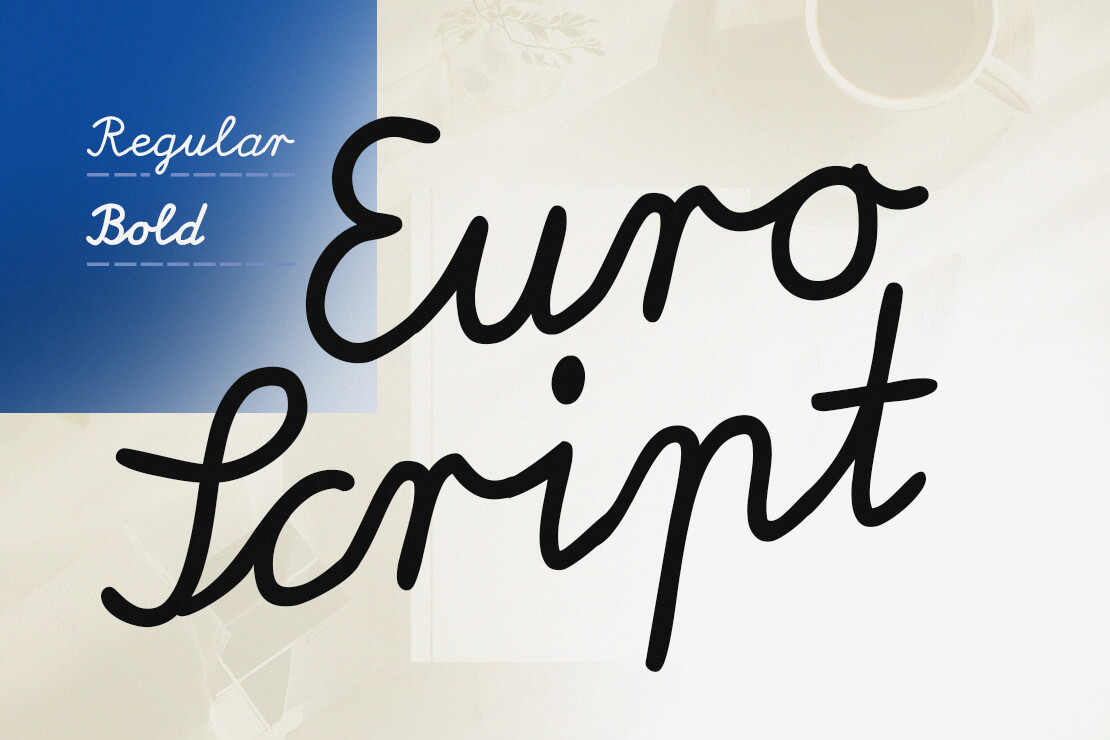
EuroScript
Mit der »EuroScript« stellt Peter Wiegel eine Schreibschrift zur Verfügung, die stilistisch auf der in Schulen gelehrten vereinfachten Ausgangsschrift basiert.
Anders als starre Lernschriften zeigt dieser Font jedoch den Charakter einer weiterentwickelten und deutlich erwachseneren Handschrift. Das Schriftbild bewahrt sich durch die verbundenen Buchstaben und leichten Unregelmäßigkeiten eine natürliche Anmutung.